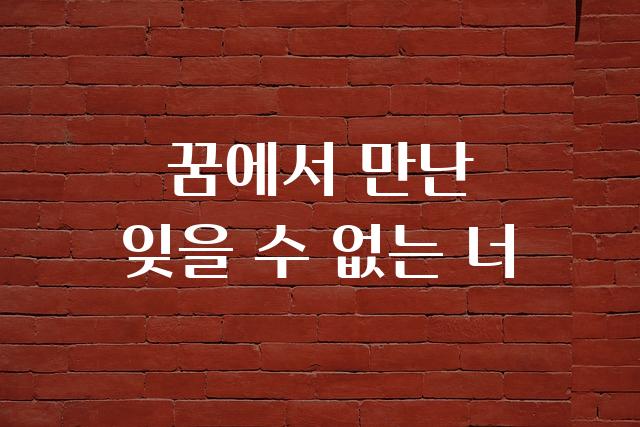
레페리포인트 Oblique은 레페리X윤디자인에 의해 제작된 기본 고딕 스타일의 폰트로, 문서 작성에 최적화된 클래식한 매력을 지니고 있습니다. 이 폰트는 현대적인 감각과 전통적인 디자인이 조화를 이루어 다양한 문서에서 유용하게 사용될 수 있습니다.
레페리포인트 Oblique은(는)
기본 고딕, 감성적인, 복고풍, 부드러움 계열의 생김새를 가지고 있으며
웹/앱 디자인, 초대장, 브랜딩 등에서 자주 활용되며, 효과적인 메시지 전달에 적합합니다.
이 폰트는 패션/뷰티, 건축/인테리어, 금융/비즈니스 분야에 잘 어울리며,
세련된, 고급스러운, 자연스러운 느낌을 담고 있는 것이 특징입니다.